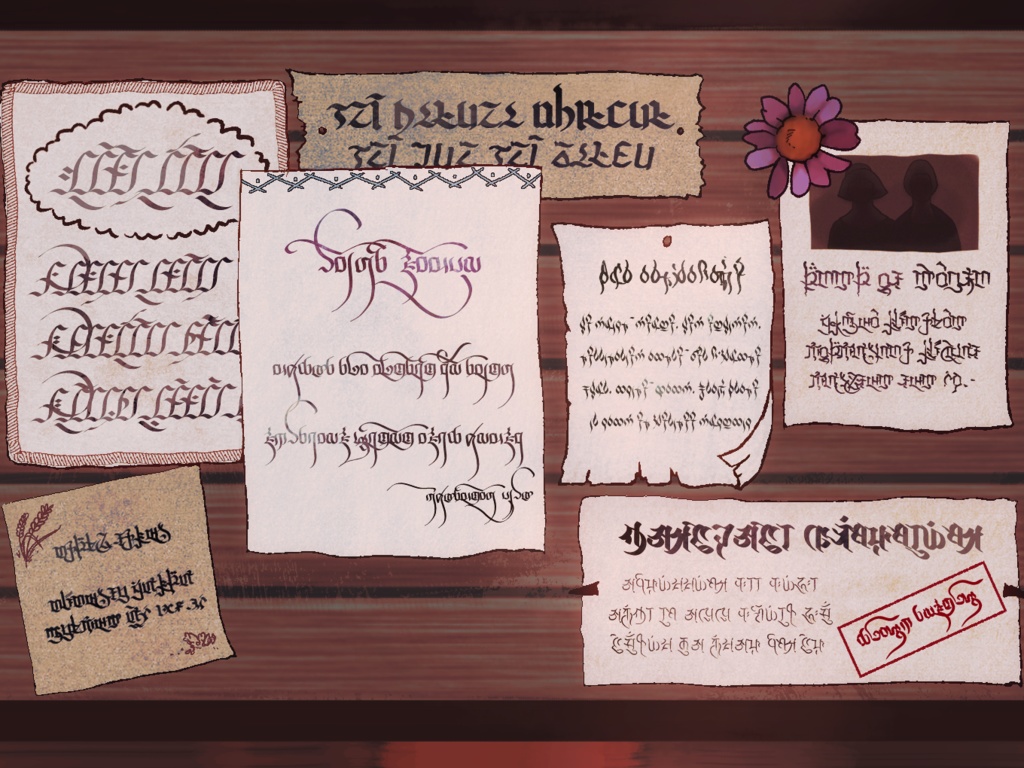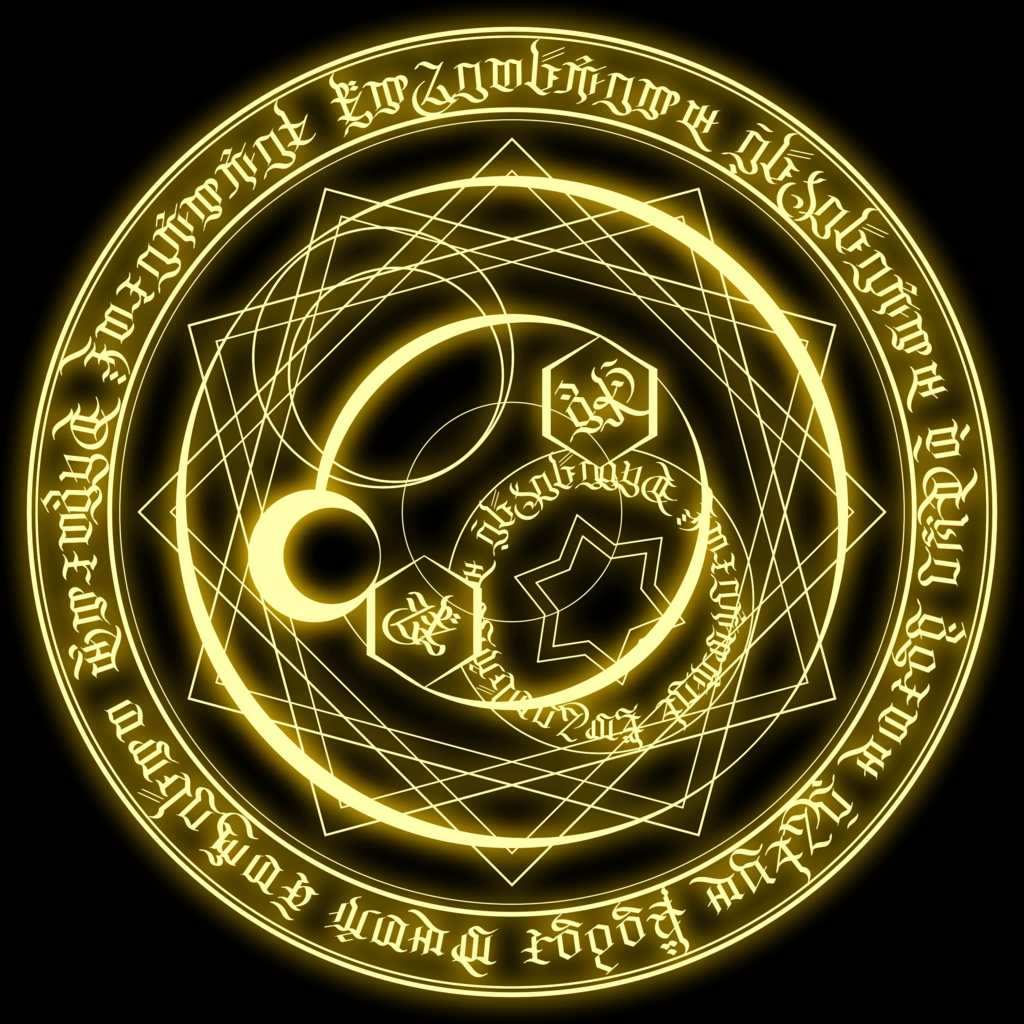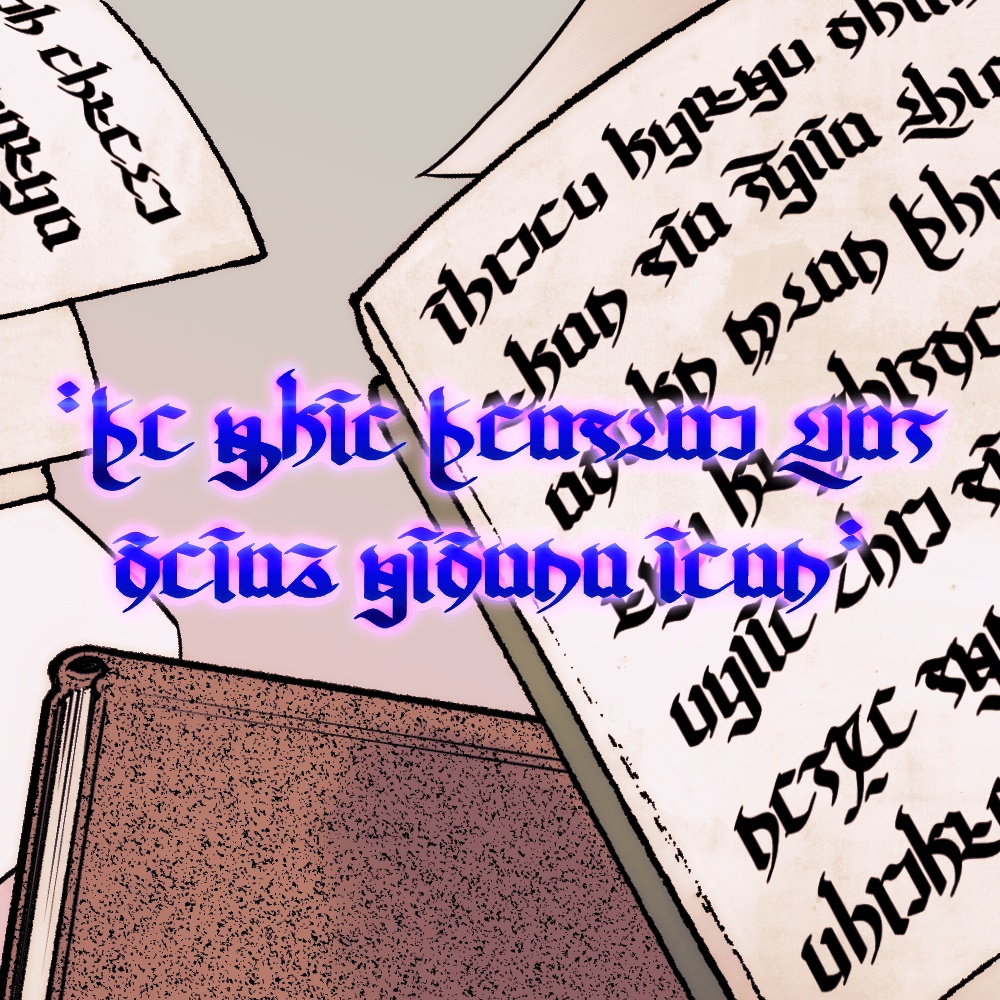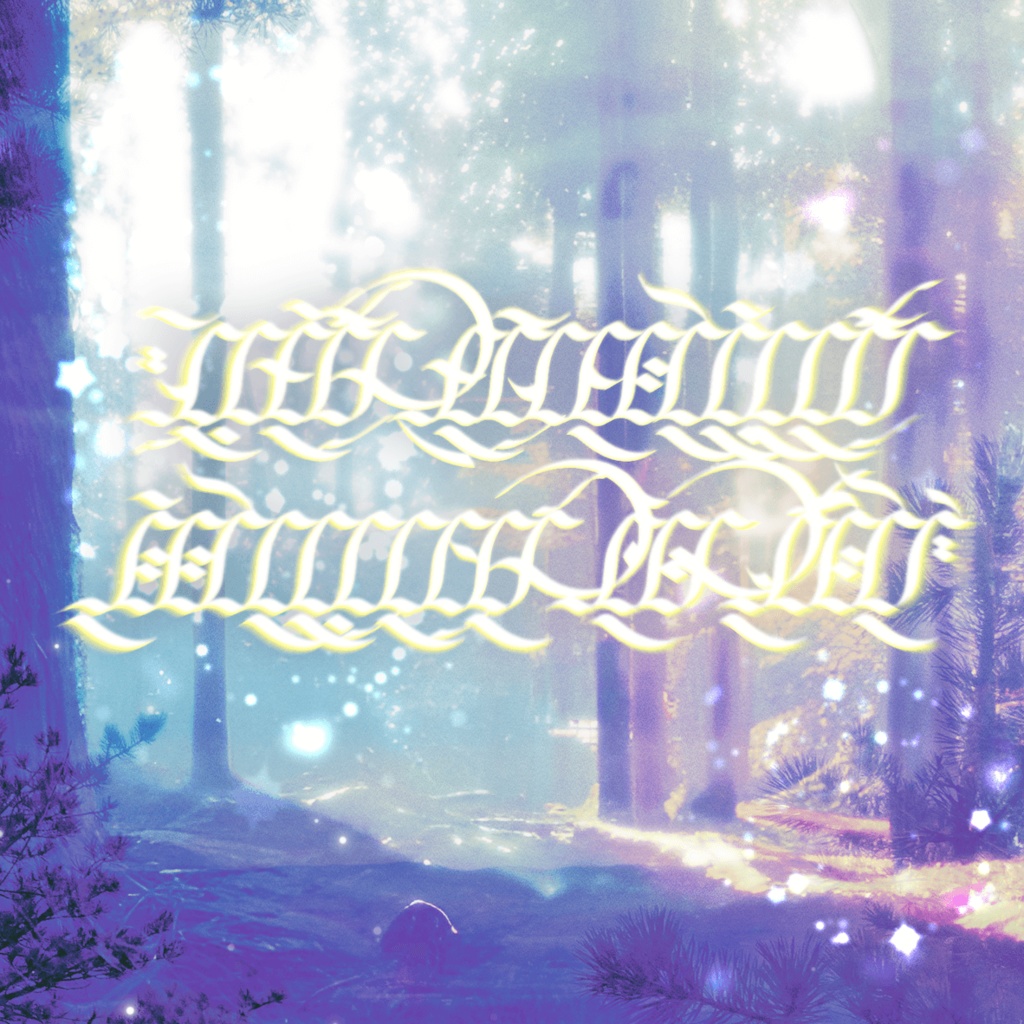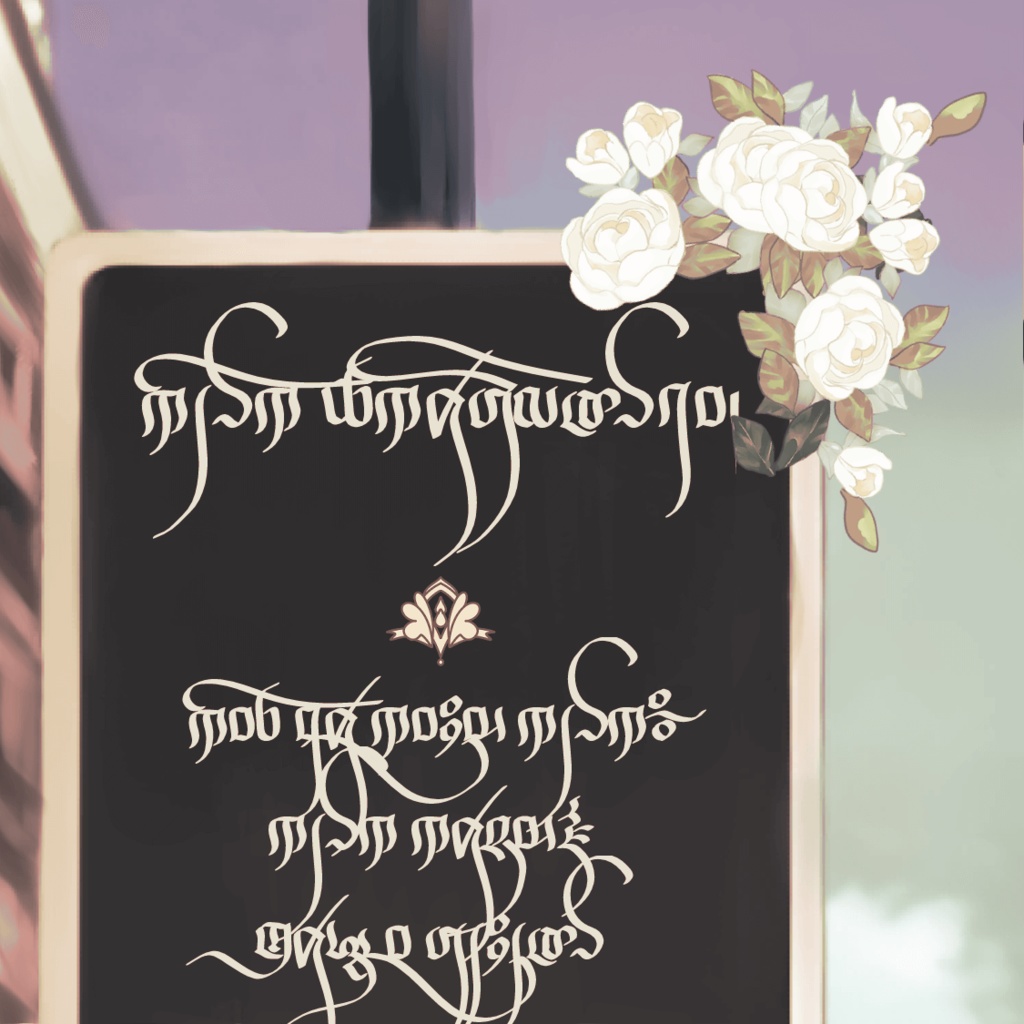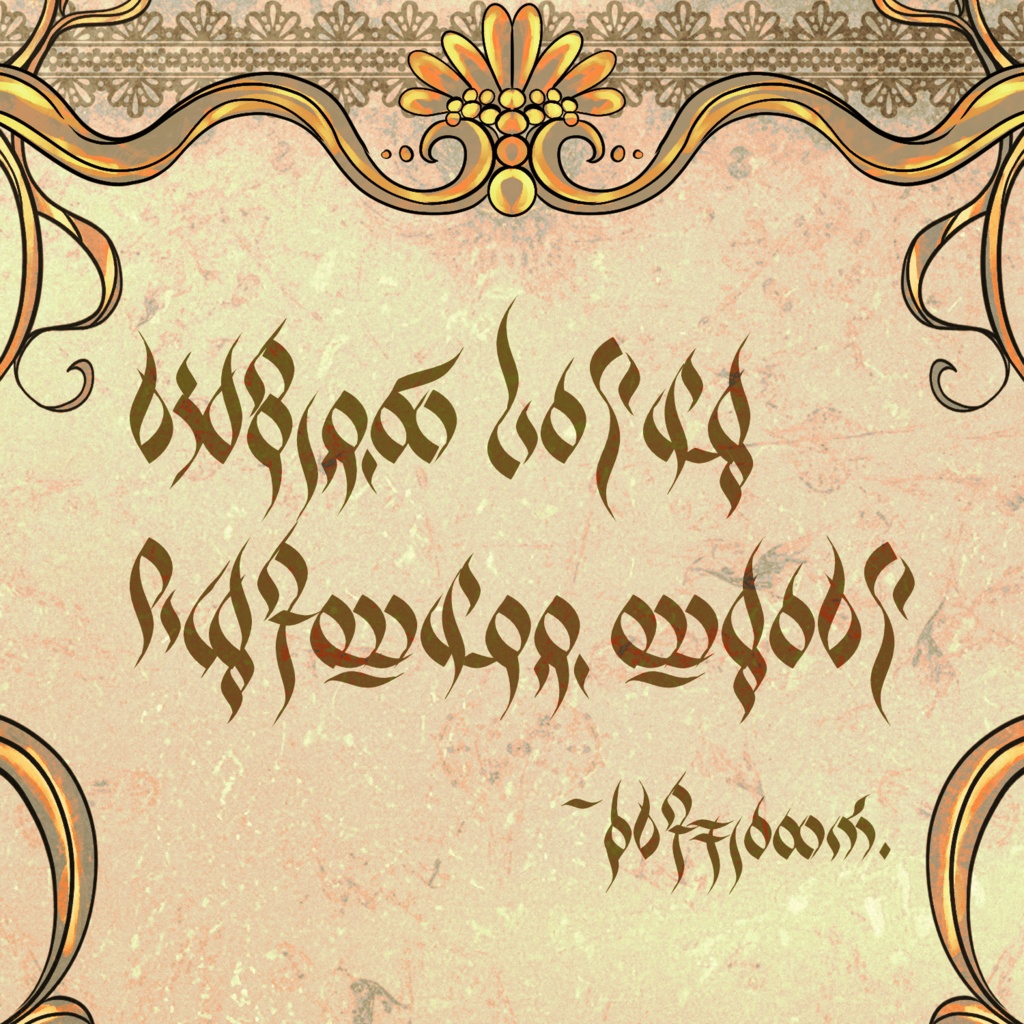
ブラックレターファンタジー文字フォント 6+6種
【紹介】 「ブラックレターファンタジー文字フォント」は、西洋ファンタジー風の架空文字をブラックレターと言うテーマで六種を集めたものです。また「ラフ」を加えたヴァリエーションも提供されます。 【収録フォント】 次の12個の.otfファイルが貰えます。各フォントの名前にELという接頭語が付き、フォント選択のとき素早い検索ができます。 EL1 Anima Enata: アニマ・エナタ (イメージ3) EL1 Anima Enata X: アニマ・エナタ・ヴァリエーション EL2 Hangela Vulgt: ハンゲラ・ヴルガータ (イメージ4) EL2 Hangela Vulgt X: ハンゲラ・ヴルガータ・ヴァリエーション EL3 Elika Runda: エーリカ・ルーンダ (イメージ5) EL3 Elika Runda X: エーリカ・ルーンダ・ヴァリエーション EL4 Chmlungma High: チョモランマ・ハイ (イメージ6) EL4 Chmlungma High X: チョモランマ・ハイ・ヴァリエーション EL5 Finfinne Orthx: フィンフィネー・オーソドックス (イメージ7) EL5 Finfinne Orthx X: フィンフィネー・オーソドックス・ヴァリエーション EL6 Askalidae: アスカリデー (イメージ8) EL6 Askalidae X: アスカリデー・ヴァリエーション 【収録文字】 半角英数字及び記号をあわせ、99個の文字が入力できます。仮名及び漢字の入力は支援しておりませんのでご了承下さい。 英文字: a-z, A-Z (56字) 数字: 0-9 (10字) 記号: . , / ? ; ! @ 等、QWERTYキーボード上の文字 (33字) EL6 Askalidae 及び EL6 Askalidae X は全角英文字をも入力できますので、クリップスタジオで縦書きすることができます。 【利用規約】 ・当フォントの著作権は作者が保持します。 ・当フォントをご購入になりました方々は商用および非商用を問わず使用できます。漫画・イラスト・デザイン・画像・動画・3Dモデル・ゲーム等の作業にてご利用できます。 ・当フォントを用いた商標・ロゴの制作を禁じます。 ・当フォントを独自の創作物と結合せずに、出版物以外のグッズを制作し販売することを禁じます。 ・当フォントのウェブサイト・サーバー・ゲーム等へのエンベッドを禁じます。 ・フォントデータの改変・転載・販売・再配布を禁じます。 【注意事項】 ・使用する際、同封されている readme.txt をお読みください。 ・使用する際、作者へ報告する必要はございませんが、おっしゃって頂けると大変嬉しいと思います。 【連絡先】 メール: lenabriongloid@gmail.com